ネオンサイン風タイトル&ロゴデザインおすすめ素材【英語フォント&ブラシ&アドオンで簡単】
ネオンサイン風の表現って、意外と便利だし、利用する機会も多いですよね。
本記事では、ネオンサイン風の表現が簡単にできるレタリング素材、フォント、ブラシ、Photoshopアドオンなどをご紹介します。
ネオンサイン風英語フォント&ブラシ&アドオンで簡単!タイトルやロゴをライトアップしよう
並べるだけ!加工なしで使えるレタリング素材
くみあわせるだけで即ネオンサインが完成するレタリング素材は、時短デザインの心強い味方です。
▼1文字ずつ背景透過PNG形式ファイルで保存された、3D電飾アルファベット素材。加工いらず&並べるだけでリアルなネオンサインがすぐに完成するスグレものです。商用利用可能で、無料ダウンロードできます。
▼好きなパーツを組み合わせるだけでOKの「Neon Alphabet Kit」!Photoshopでネオンの色やライトのON・OFFが自由に設定できます。背面のケーブルやフレームなどのデータもついてきます。
あなたのデザインをネオンサイン風に変換!Photoshopアドオン
あなたがデザインした図形や文字をネオンサイン風に変えてくれるPhotoshopのアドオンを紹介します。
▼同じ色のネオンでも白っぽいものや淡い光のものなど数種類から選べる「The Neon Toolbox」。よりリアルに見せるための背景テクスチャやケーブルなどの機材要素も多数収録しています。
▼自分で描いた図形や文字をあっというまにネオンサイン風にしてくれる、便利なPhotoshopアドオン「Neon Layer Styles」。明るい色やパステルカラーなど、自由に選べます。
一からのデザインは不要!ネオンサイン風フォント
こちらで紹介するフォントはネオンサインの電灯形状をモチーフとしたフォントです。これらのフォントをベースにPhotoshopで加工すると画像のような、まるで本物のネオンサインのようになります。
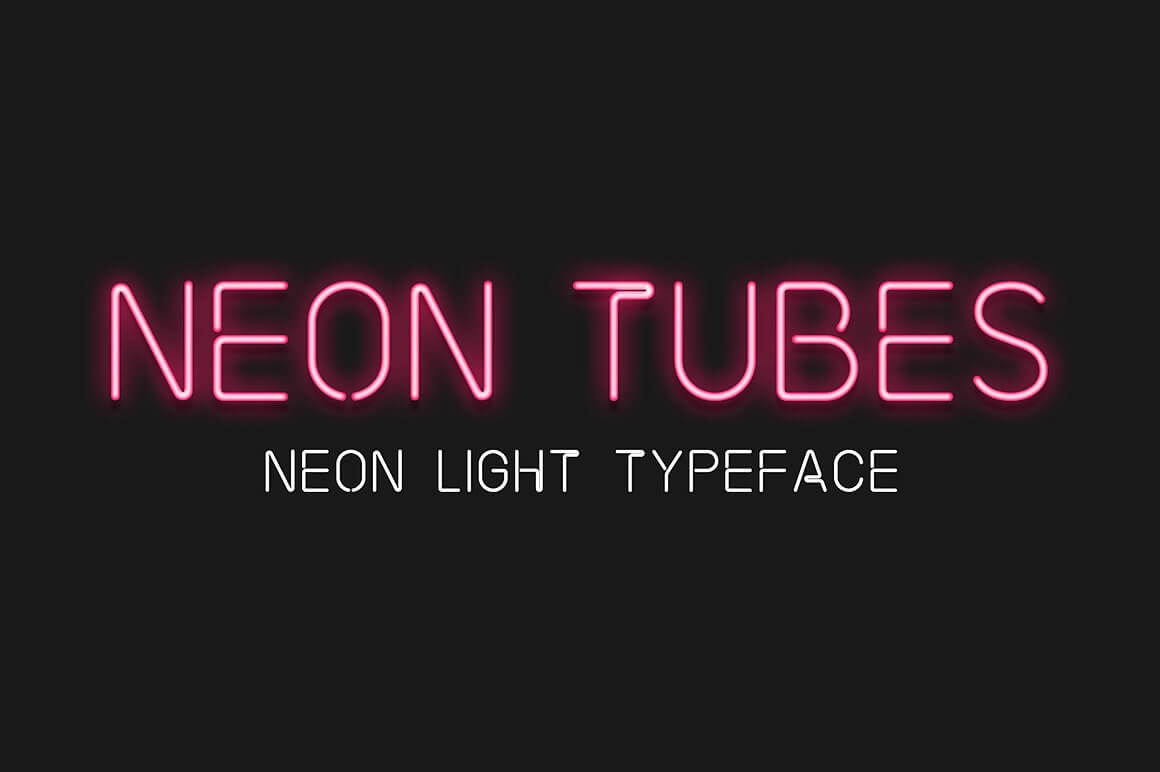
▼ネオン加工済みのSVGフォントを収録した「7even SVG – Urban Neon Font Pack」。カット入りとカットなしの2バージョンがあります。
描くだけで簡単!ネオンサイン風ブラシ
ネオン風のブラシで文字を書けば、ネオンサイン風の表現も簡単です。
▼ライトのように光る27種類のProcreateブラシが収録されたLights Procreate Brushes。詳細ページでは全ブラシの見本が確認できます。
▼30種以上のネオン風プロクリエイトブラシとカラーパレットを収録した「30+ Procreate Neon Brushes」。色や太さも自由に変更できます。
▼「Neon Affinity Brushes」はAffinity Designerで使えるネオン風ブラシ。ライトの陰影別にブラシが用意されています。